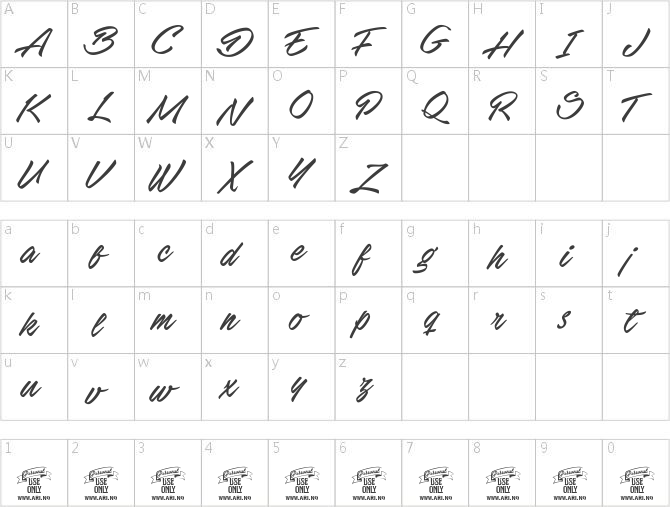
Stackyard_PERSONAL_USE
Stackyard_PERSONAL_USE介紹
Stackyard_PERSONAL_USE字體字庫是一款讓人賞心悅目、百看不厭的英文字體,適合各類廣告和產品包裝設計應用,字體大小0.13MB,格式為ttf字體,上傳用戶是手機洗相,作者/版權方為未知